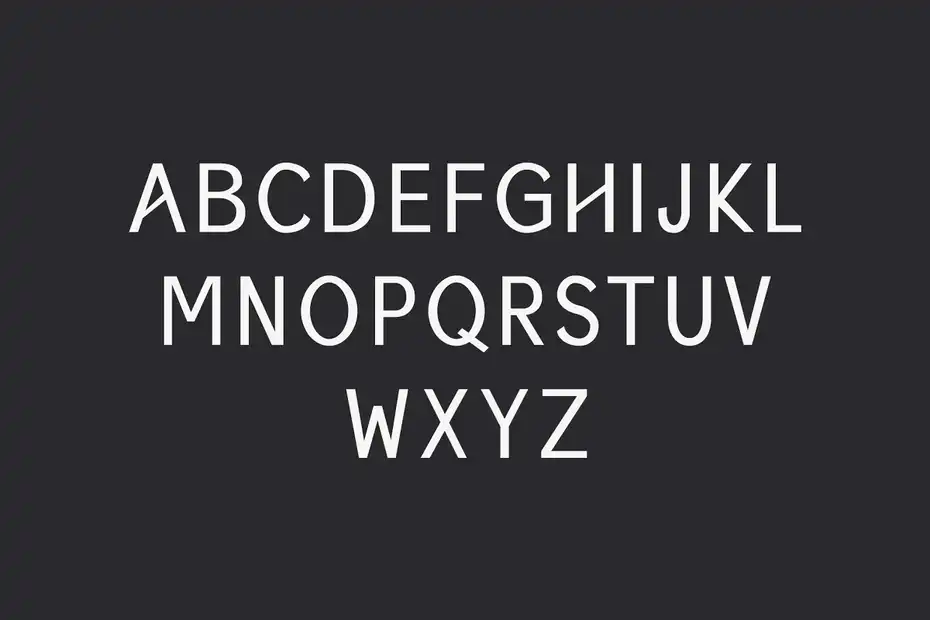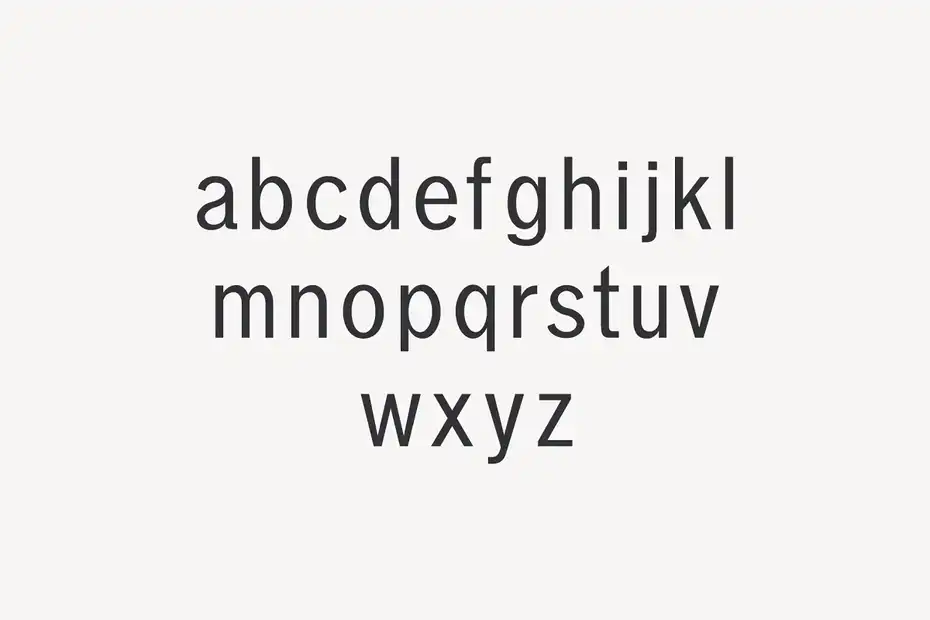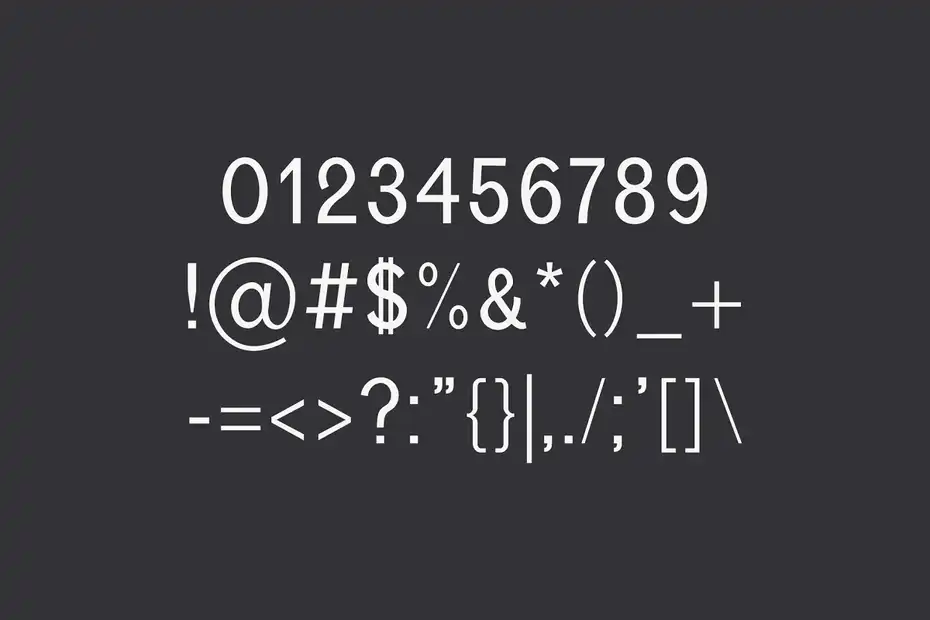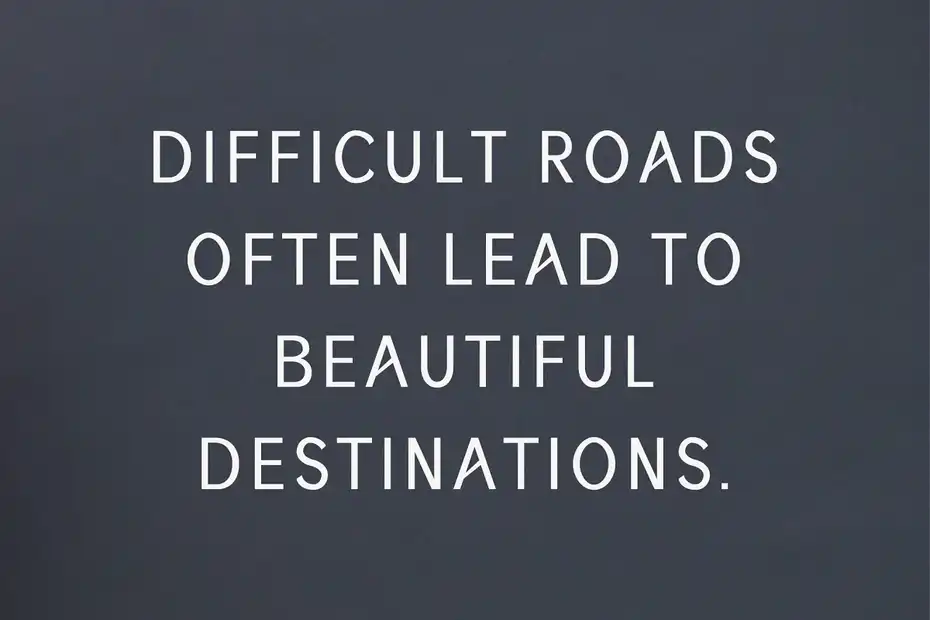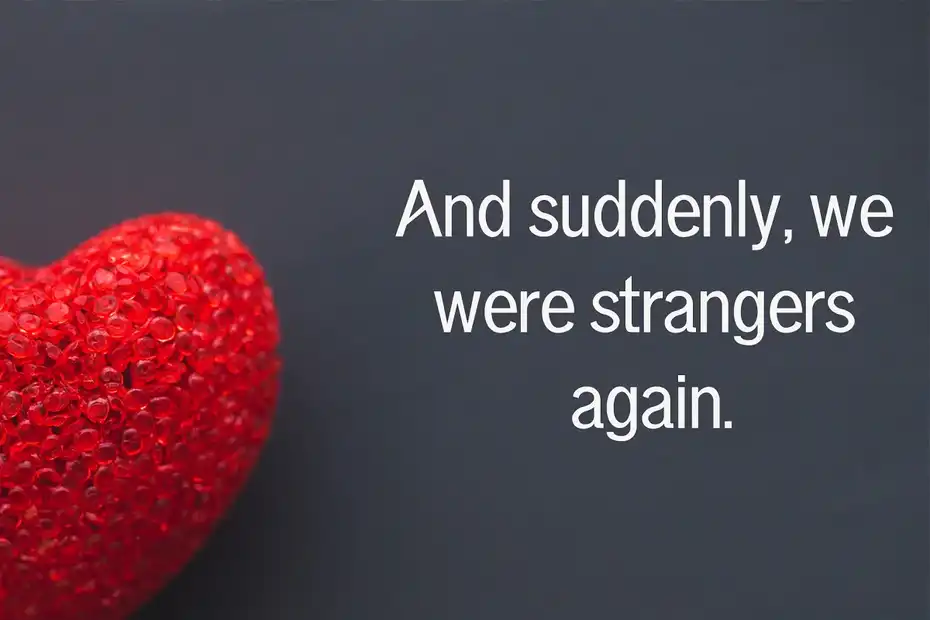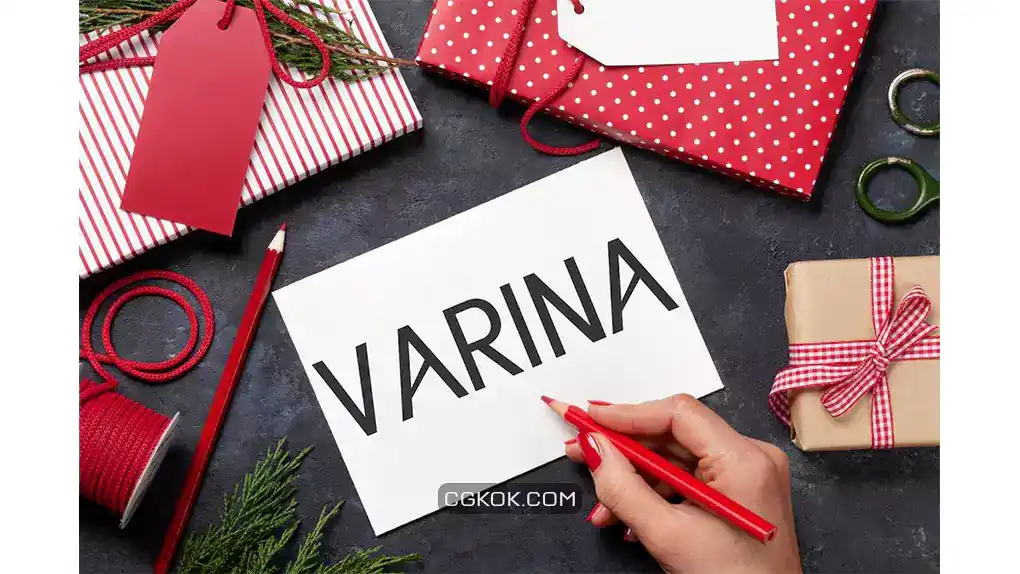
دانلود فونت انگلیسی مدرن Varina Sans Serif Font Family
فونت انگلیسی مدرن Varina Sans Serif Font Family : این مجموعه شامل یک فونت انگلیسی هندسی مدرن است که برای مجلات، بروشور، طرح‌ بندی‌ های سرمقاله، لوگو، سرفصل‌ ها، پوستر، برچسب، آگهی روزنامه، بنر، قالب‌ و غیره مناسب میباشد.